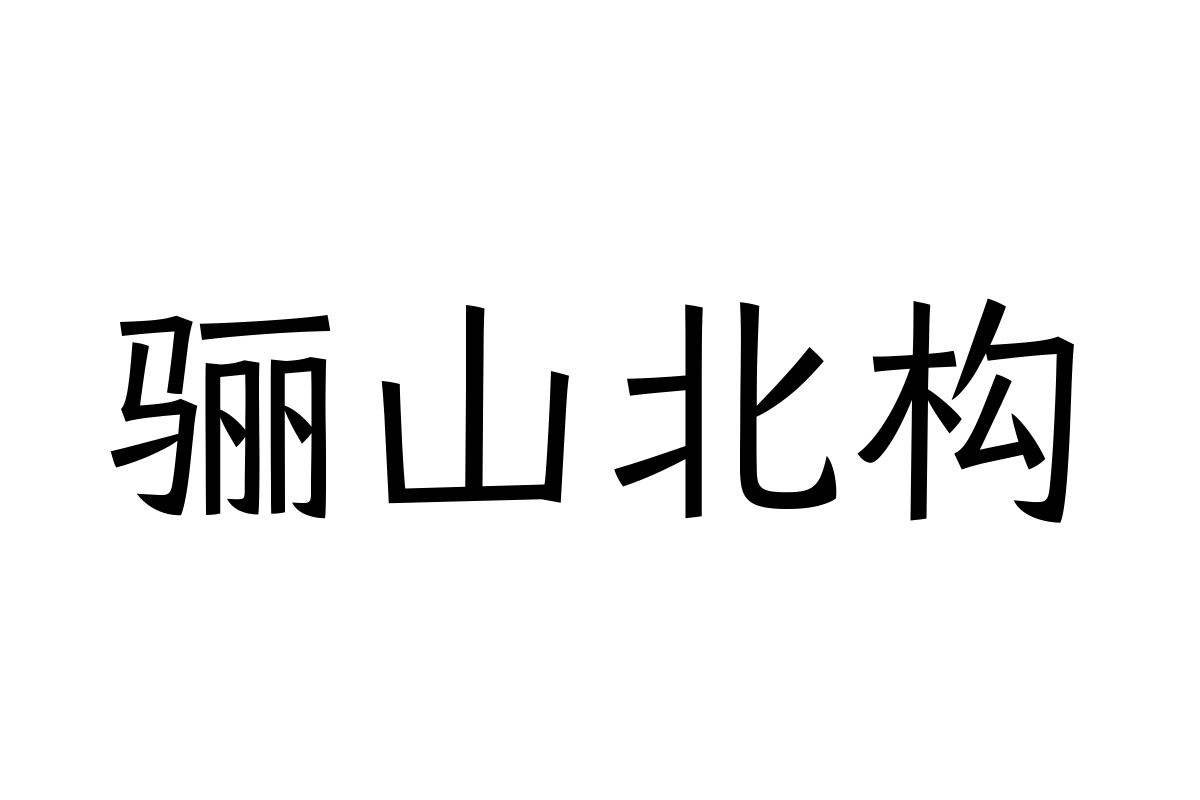
汉仪将军45w是一款由汉仪公司设计的中文字体,具有独特的设计风格和广泛的应用场景。这款字体采用了现代简约的设计理念,线条流畅,字形规整,适合用于各种文字设计项目,如广告、标识、报纸、杂志等。
汉仪将军45w的笔画粗细适中,既有力度感又不失柔和,使得整体视觉效果更加和谐。同时,这款字体还具有一定的可读性,适用于正式场合的文字展示。
此外,汉仪将军45w还具有较好的适应性,可以在不同的应用场景中展现出不同的风格。例如,在需要强调文字力量感的场景中,可以选择使用粗体或加粗的汉仪将军45w;而在需要展现柔和美感的场景中,可以选择细体或细黑的汉仪将军45w。
总的来说,汉仪将军45w是一款实用且具有较强可塑性的中文字体,适用于多种文字设计需求。